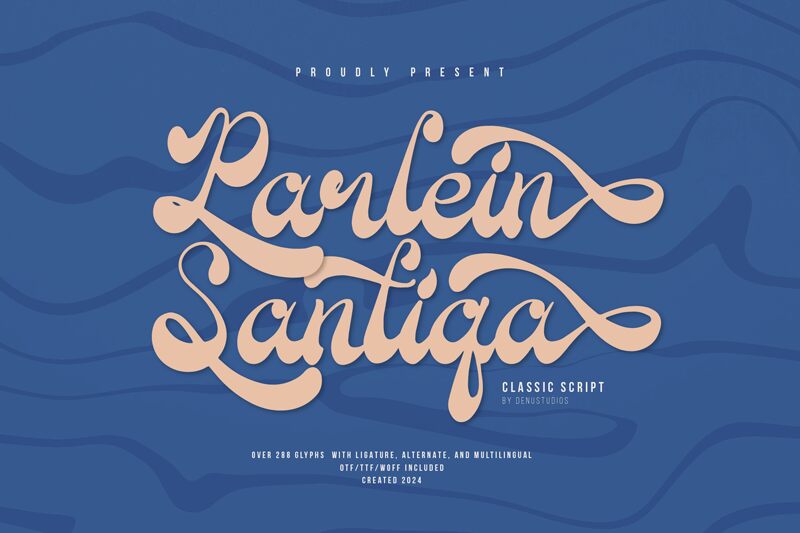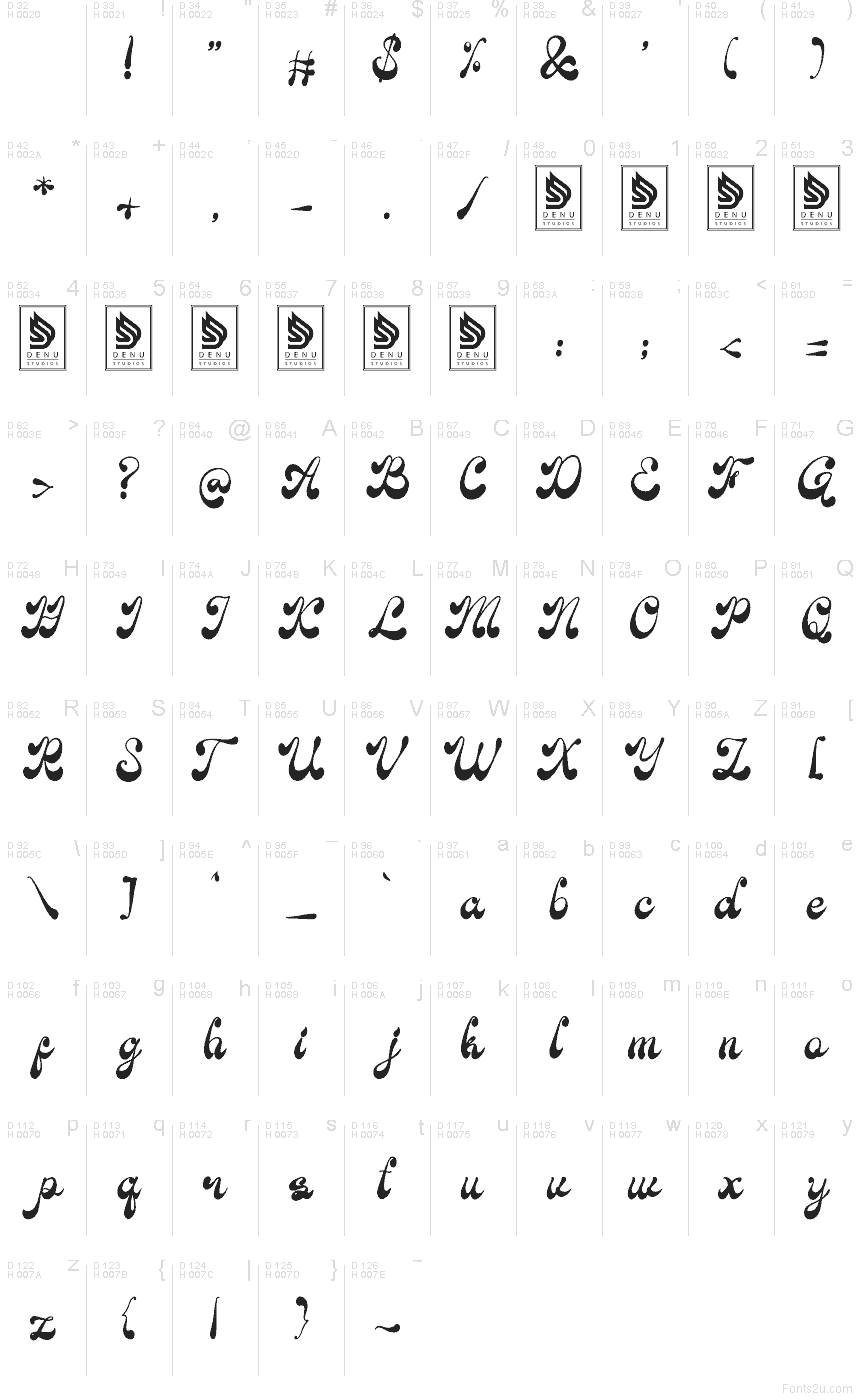
Parlein Santiqa de Denustudios es una tipografía script de pincel gratuita con un suave aire retro a rótulo pintado a mano. Sus letras oscilan entre trazos anchos en forma de gota y curvas finas de enlace, lo que le da a la fuente un ritmo fluido que resulta elegante sin perder la naturalidad.
Encaja perfectamente en branding, packaging de boutique, menús de cafeterías, invitaciones y titulares editoriales de belleza donde una fuente gratuita pueda añadir un toque de distinción sin volverse demasiado recargada. Dado que los trazos se ensanchan y afinan de forma tan marcada, también funciona muy bien en logotipos cortos, tarjetas de título y monogramas, donde el movimiento de las letras lleva el peso del diseño.